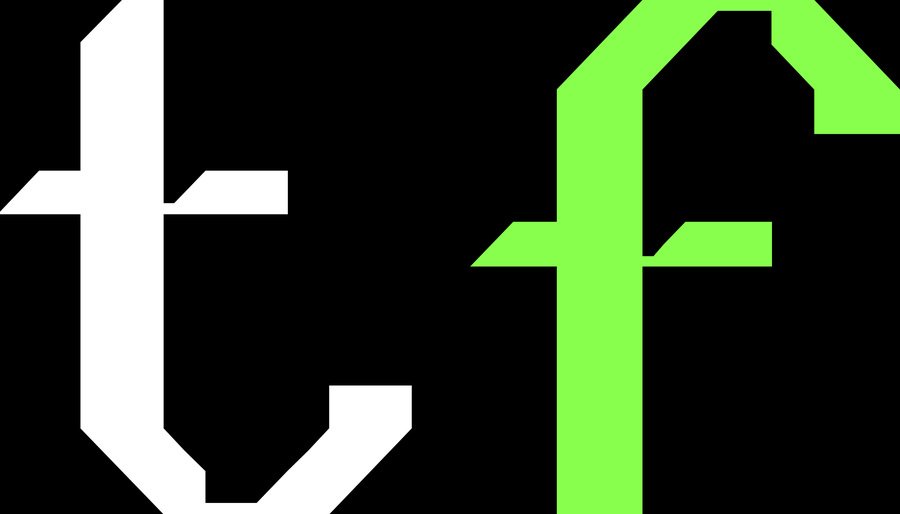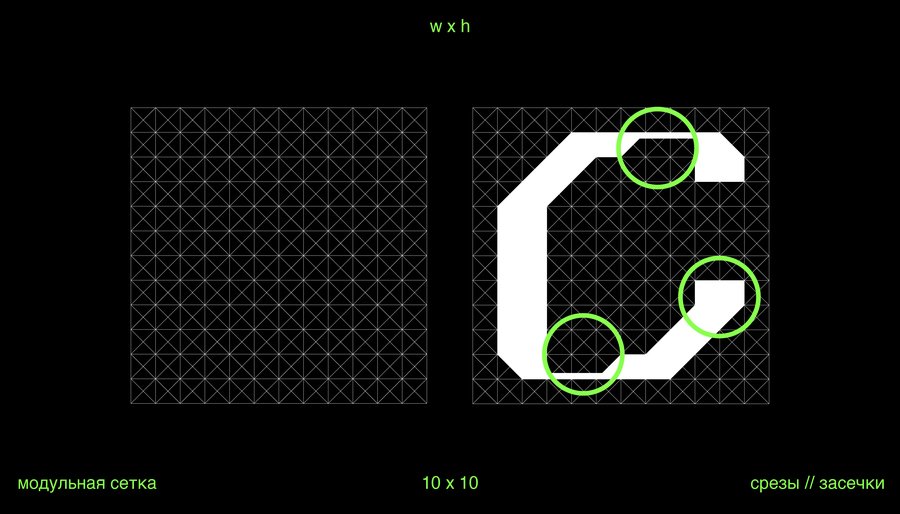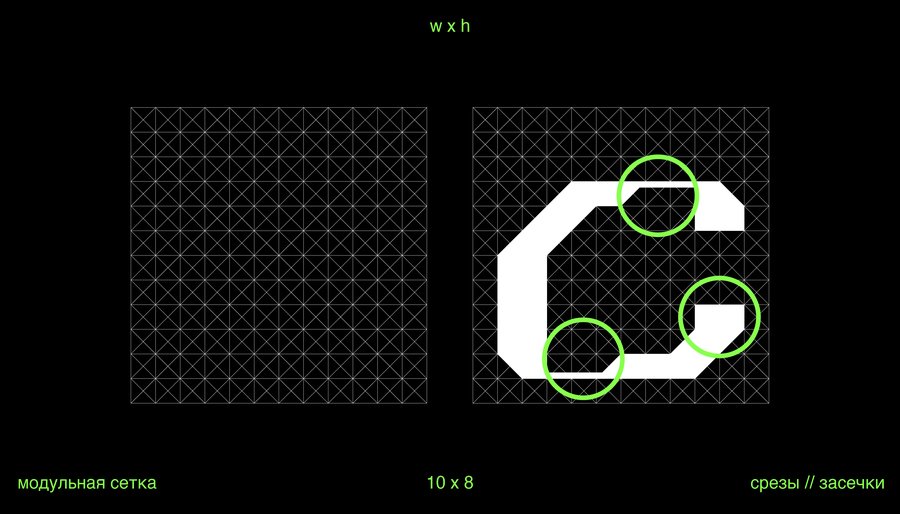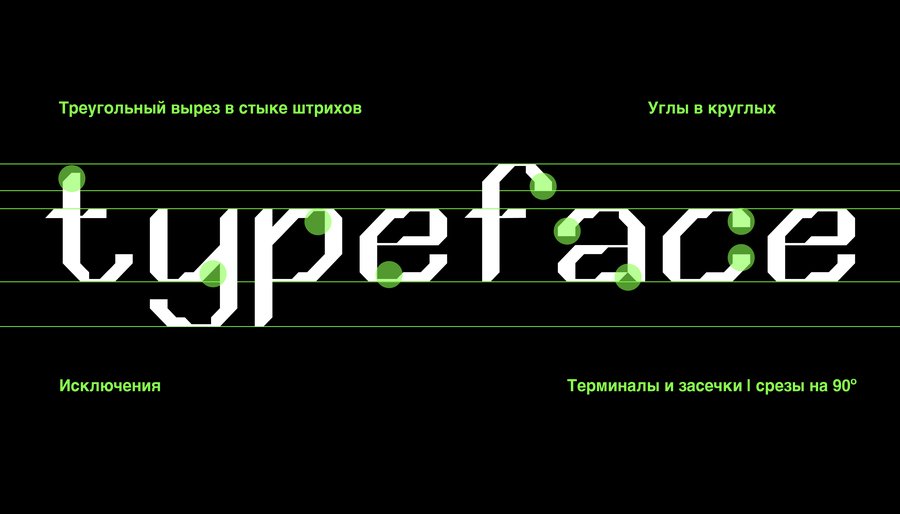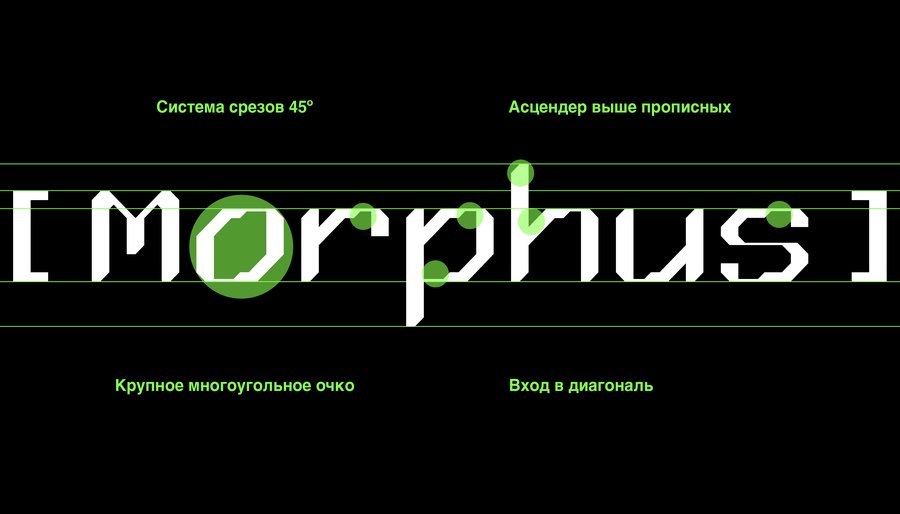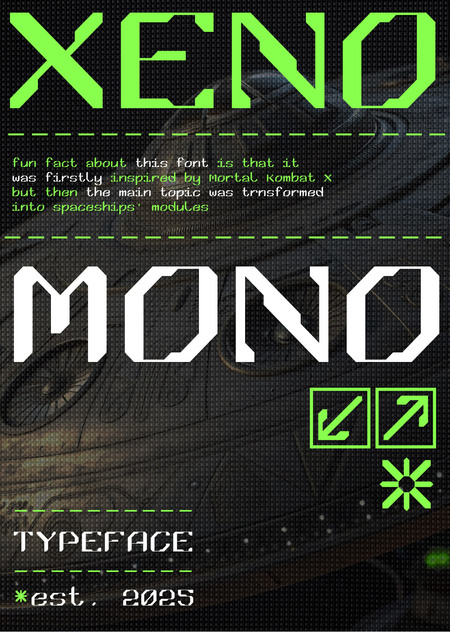
XENO MONO Typeface
[лат. xeno — чужой]
Акцидентный шрифт для проектов на тему космоса, Science-fiction проектов и геймдизайна, вдохновленный строением модулей, обшивающих корпусы космических кораблей.